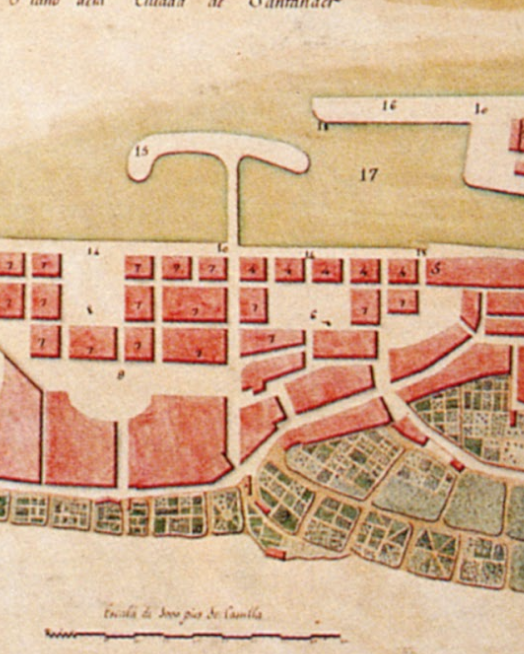
Calle Martillo a comienzos de los 90s
Imagen del paisaje visual de una calle tan característica como ha sido la Calle Martillo (hoy Marcelino Sanz de Sautola). Algunos rótulos son tan icónicos como su historia. Como por ejemplo esa mítica hamburguesería llamada «Happy Burger» (cuántos cumpleaños habremos celebrado allí antes de la llegada de las grandes cadenas…) y poder ver los estudios de Antena 3, el periódico «El Alerta», el bar Nido y otros comercios del barrio, así como la sede de la Fundación Botín.
PD: ¿Sabes por que se llamaba Calle Martillo? ahí va la curiosidad: Se la conocía así por la dársena en forma de martillo que desembocaba al puerto. En este mapa de Santander, realizado por José Fernández Alday en 1793, se ve perfectamente ese detalle.